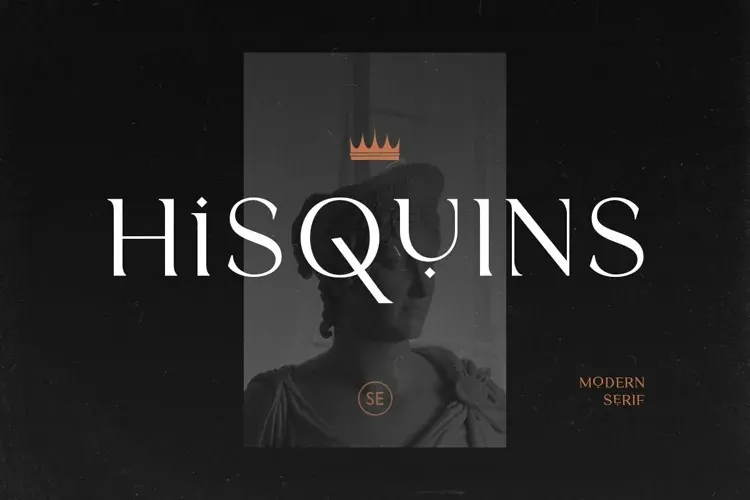
Hisquins Font
A Hisquins Font é uma elegante tipografia serifada que traz um toque de luxo ao seu design. Seu estilo refinado é complementado por pontos finos e aguçados, criando um toque moderno e legível que remete à estética persa. Perfeita para logotipia, a Hisquins Font também atende bem como fonte de marca, permitindo combiná-la com letras maiúsculas e minúsculas para criar um logo mais único e chamativo. Além disso, suporta várias línguas, tornando-a uma opção versátil para qualquer projeto gráfico. Este novo design da Hisquins pode adicionar profundidade e sofisticação a seu trabalho de design.